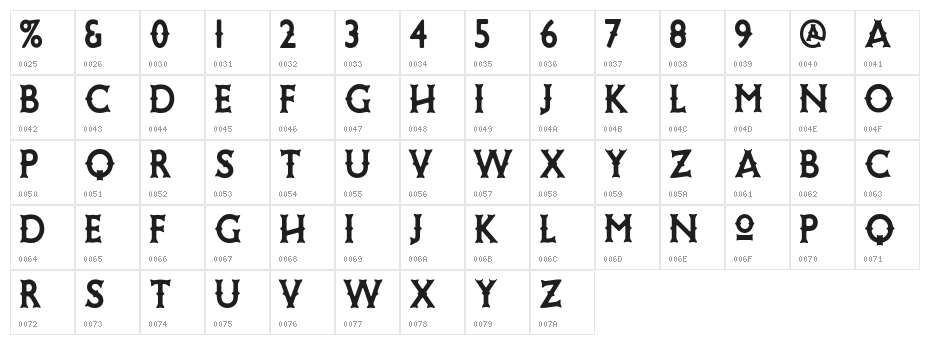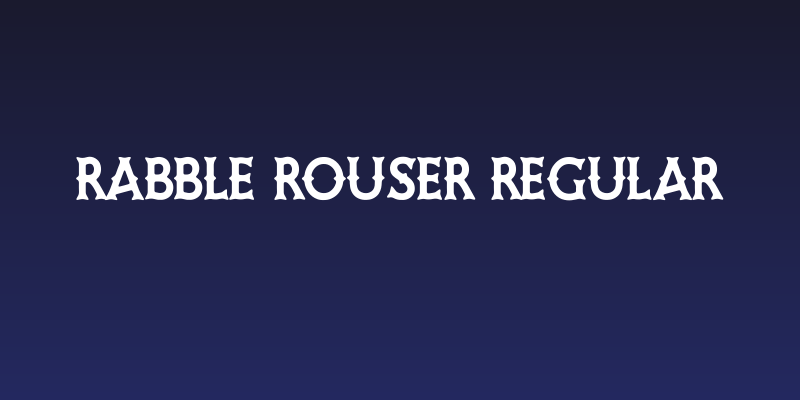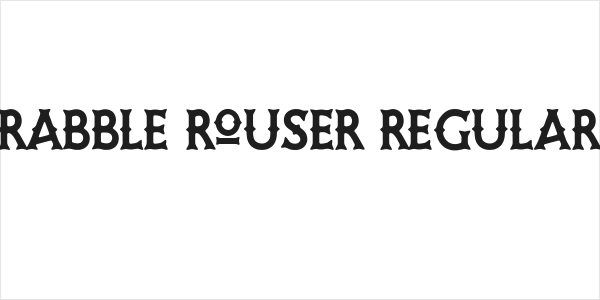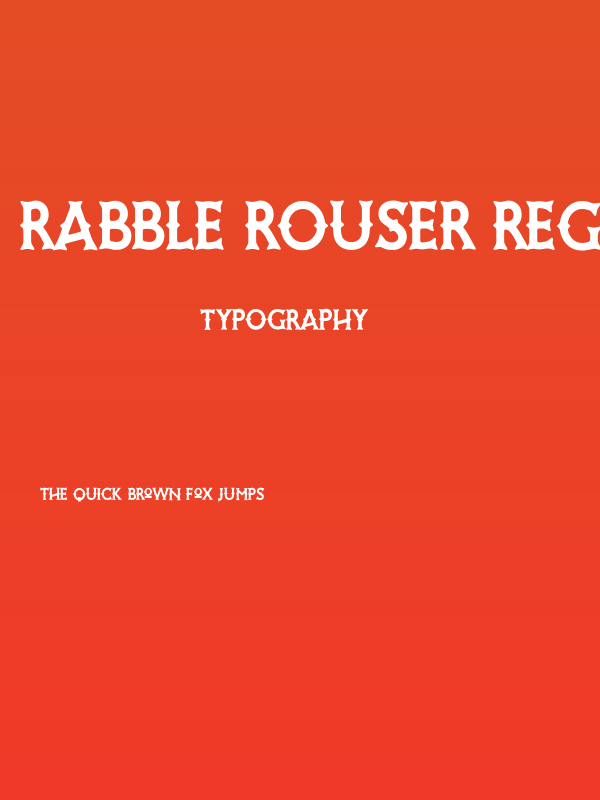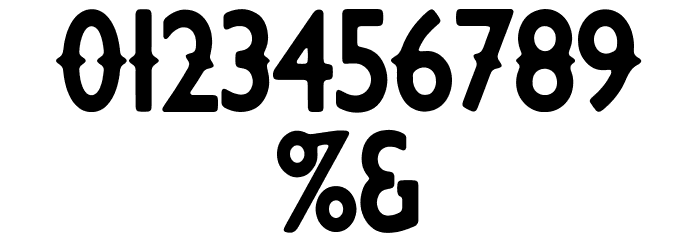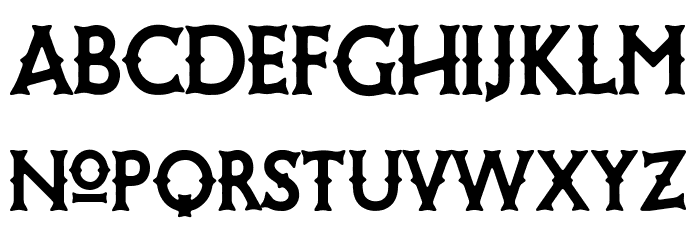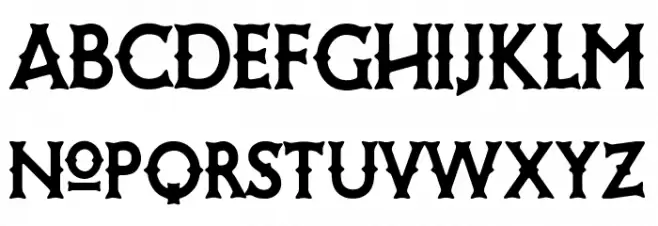
Rabble Rouser Regular Font
| Proiecte propuse | Ideal for posters, album covers, Halloween-themed designs, and any project needing a dramatic, eye-catching typeface. |